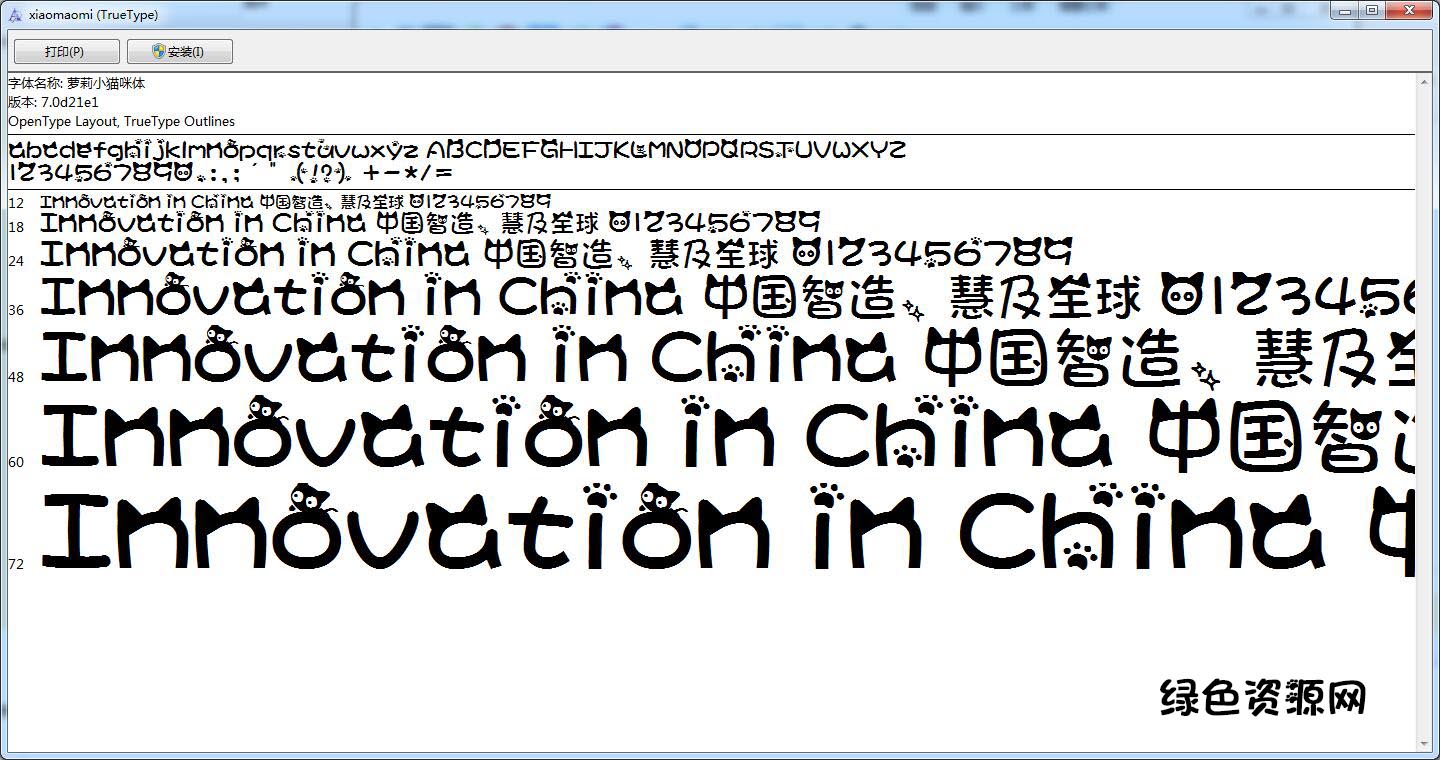
蘿莉小貓咪字體是款超萌的卡通字體應(yīng)用。小編安裝了這款字體,輸出的文字真的萌呆了!不管你是打英文還是中文,都可以將文字變成貓咪卡通風(fēng)格!快來(lái)綠色資源網(wǎng)下載體驗(yàn)吧!
蘿莉小貓咪字體是一款卡通風(fēng)格的字體,為用戶提供了中英文字體,字體增加了可愛(ài)的小貓裝飾元素,打出的文字極具卡通性!